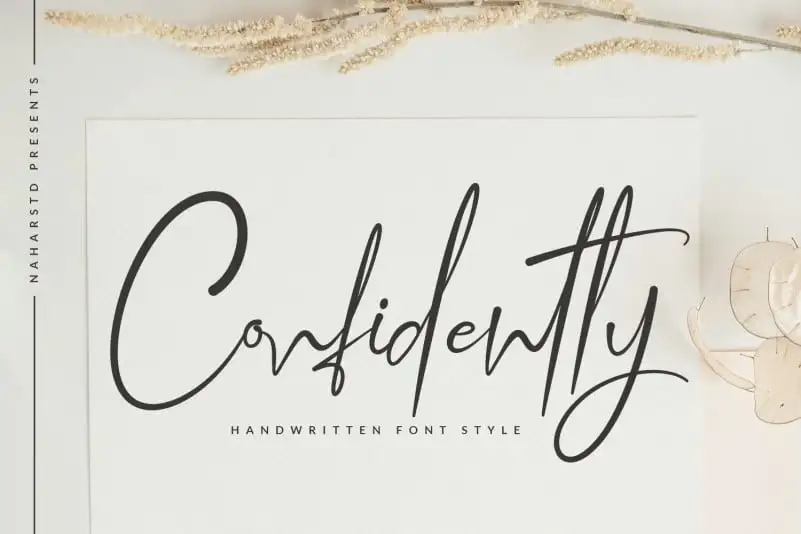
Confidently – Handwritten Font – Download Grátis
A fonte ‘Confidently – Handwritten Font’ é perfeita para projetos que buscam um toque elegante e autêntico de escrita a mão. Essa fonte única oferece um estilo fluido e encantador, ideal tanto para criar logotipos ou trabalhos de identidade corporativa quanto para designs de embalagens de produto ou materiais promocionais como mugs e banners. Suave mas poderosa, ela se destaca em qualquer projeto que precise de uma pitada de personalização e encanto. A fonte é perfeita tanto para criações simples e deslumbrantes quanto para design gráfico complexo, garantindo a unificação perfeita entre texto e imagem em todos os seus projetos. Idealmente utilizada em design de móveis de casa, embalagens de produto, capas de livro, cartões de nome, convites e cartões de visita, etiquetas e até mesmo em trabalhos fotográficos e eventos especiais, a fonte ‘Confidently – Handwritten Font’ tem um apelo universal que se encaixa perfeitamente com qualquer trabalho gráfico. Suavemente delicada e robusta ao mesmo tempo, ela é uma escolha ideal para aqueles que buscam uma pontuação de escrita pessoal em seus projetos, criando um toque diferenciado e encantador nos resultados finais.